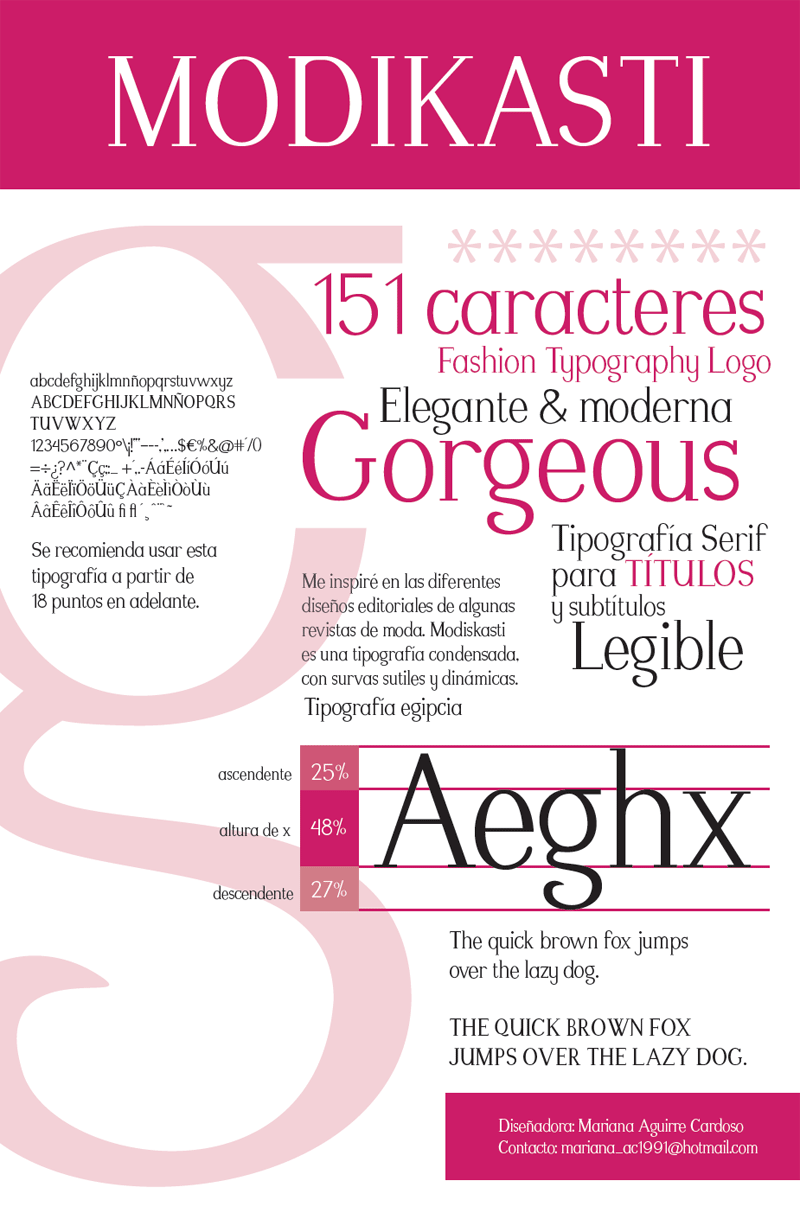
Font name: | Modikasti |
Author: | Mariana Aguirre |
Note by Mariana Aguirre | |
Es un tipografĂa serif, inspirada en la moda. es moderna y divertida. Le puede dar ese toque diferente cualquier documento. |